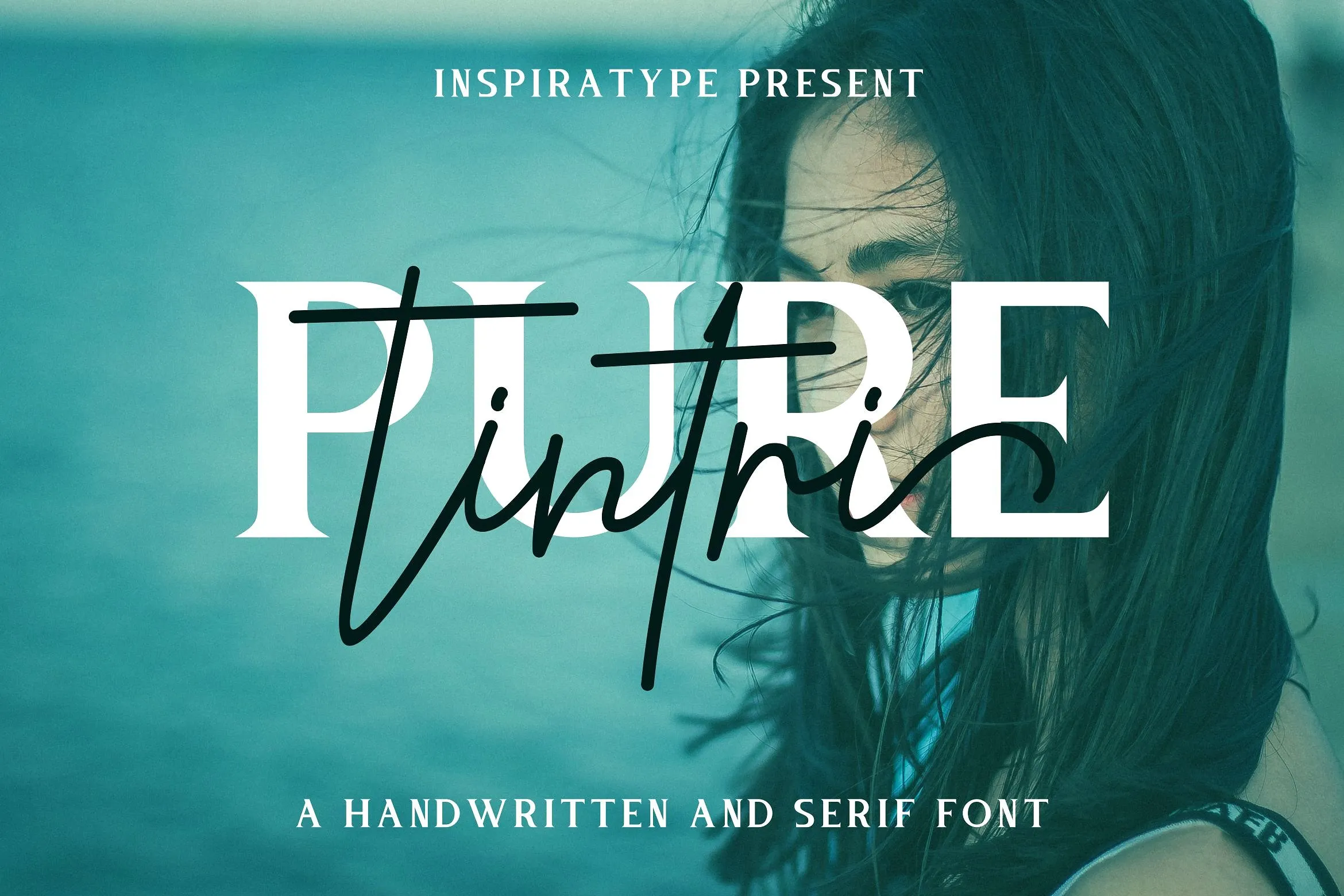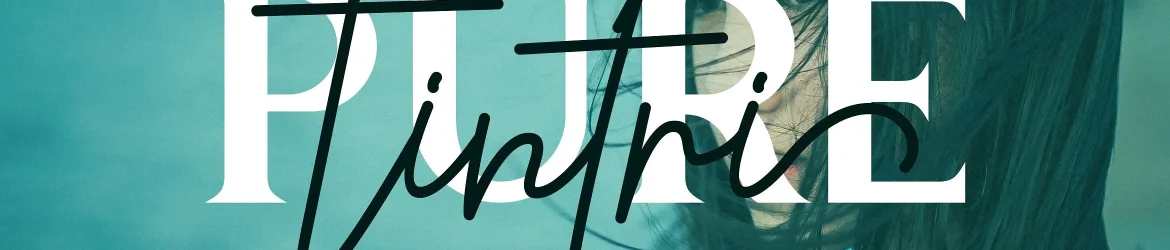
Tintri Pure Font Duo – Download Grátis
A fonte Tintri Pure Font Duo é uma nova dupla de fontes cursivas e serifadas criada pela Inspiratype, inspirada nos clássicos cartazes modernos. Composta por um conjunto completo que inclui letras maiúsculas, minúsculas, números e pontuações, esta fonte foi feita à mão para a exibição de visual gráfico poderoso. Através da opção de alternativas abertamente personalizáveis do tipo OpenType, ligaturas comuns e até mesmo asas adicionais nos caracteres, você pode personalizar seus designs conforme seu desejo. Com estas características únicas, Tintri Pure Font Duo é perfeito para uso em logotipos, cartões de visita, outdoors, design de roupas, etiquetas e muito mais.